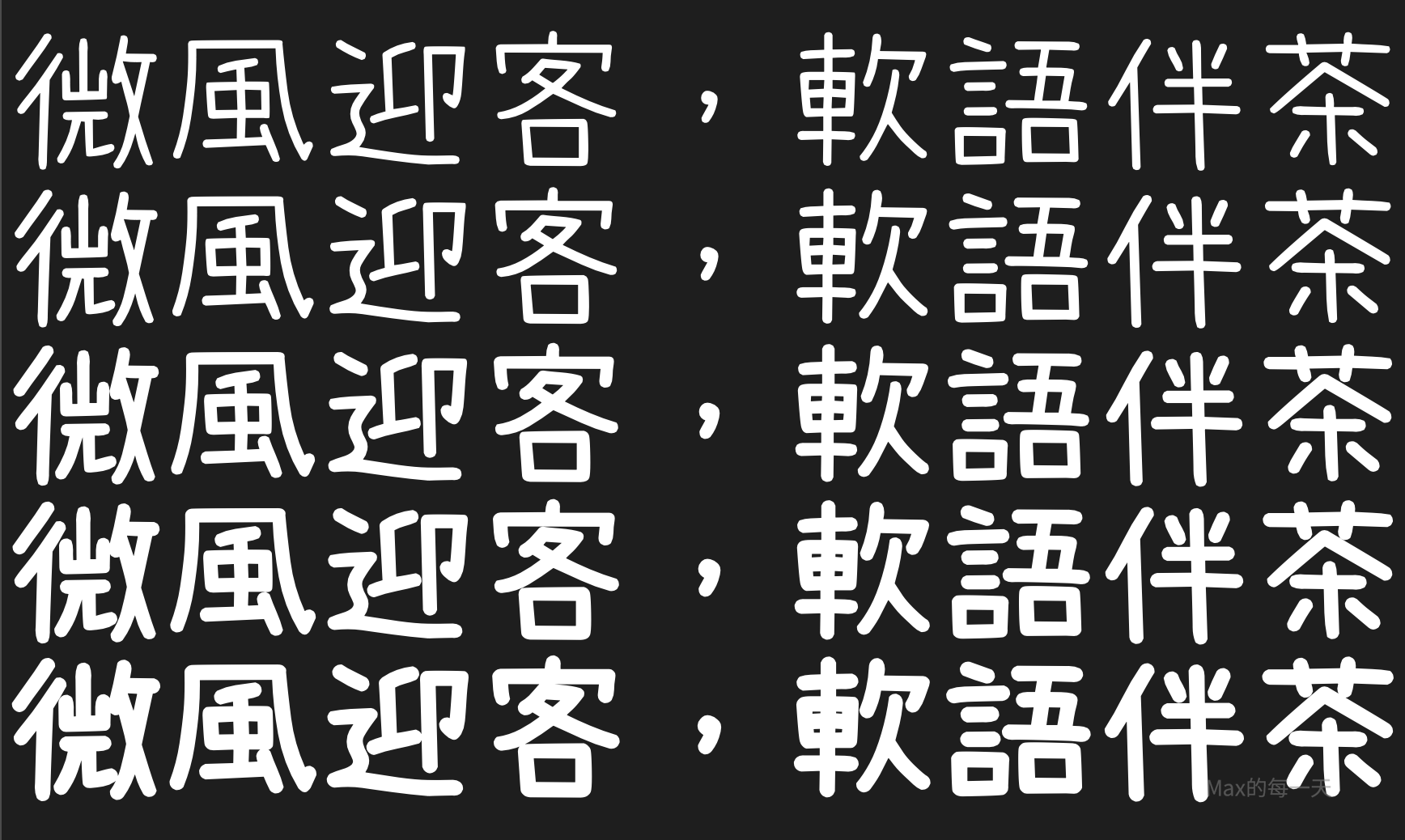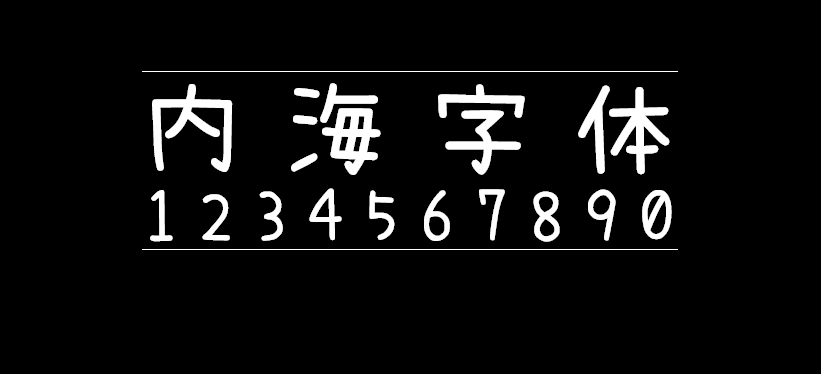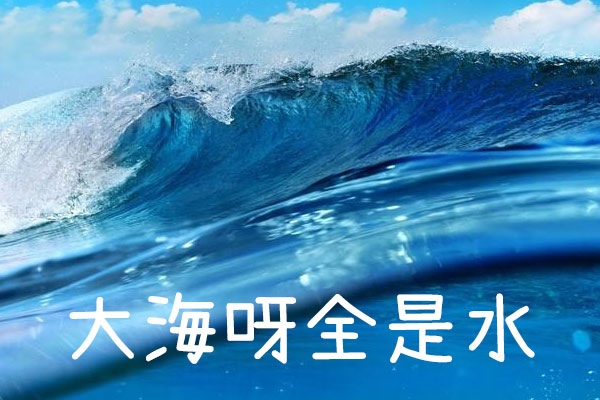
内海字体
内海字体(NaikaiFont 内海フォント)是台湾字体设计师Max基于日本濑户字体(免费商用)进行修改而成的一款免费商用字体。目前包含了31,933个字符,基本上涵盖大部分的简体中文,繁体中文,日文,英文等,而且增加至5种字重,实在是一款非常不错的字体。
字体特色:
1、补齐台湾教育部列出的4,808个常用字,内海字体在原本的濑户字体架构下,内海字体增加65字。补齐了台湾教育部列出的4,808个常用字。
2、字体增加至5种字重,原本的濑户字体放在Regular字重里,现在透过电脑程序自动产生ExtraLight、Light、SemiBold、Bold第4个新的字重。在ExtraLight和Light字重是把原本的濑户字体微微调细一点点。在Light的字重里,可能会因为笔划太细造成某些笔画消失。而在SemiBold和Bold的字重里,可能会因为笔划太粗造成某些笔画重叠难以识别,有粗体字的需求,可以先选择使用Bold字重看看,如果发现效果不如预期,再改用SemiBold字重。 因为是用程序自动生成的字体,所以不能确保自动产生出来的字重里每一个都是完整的字,毕竟程序会误判是常有的事情,所以不是在Regular字重里的笔划可能会消失。大家使用时请注意。
3、清除濑户字体里空白的文字,濑户字体setofont里有很多空白的字,会造成无法让系统自动用预设字体来补字,现在已清除空白的文字。
4、调整标点符号位置,濑户字体的全形标点符号针对日本做设计,现在调整为台湾常见的置中用法。半形的backslash,调整为非日本地区用法。
5、增加《台湾闽南语推荐用字700字表》里出现的中文字,在原本的濑户字体架构下,内海字体增加47字。
6、增加部分粤语字,在内海字体增加40字粤语字。
7、合并原作者濑户的扩充字,原作者原本另外放的扩充字型档在合并后,在内海字体增加303字。